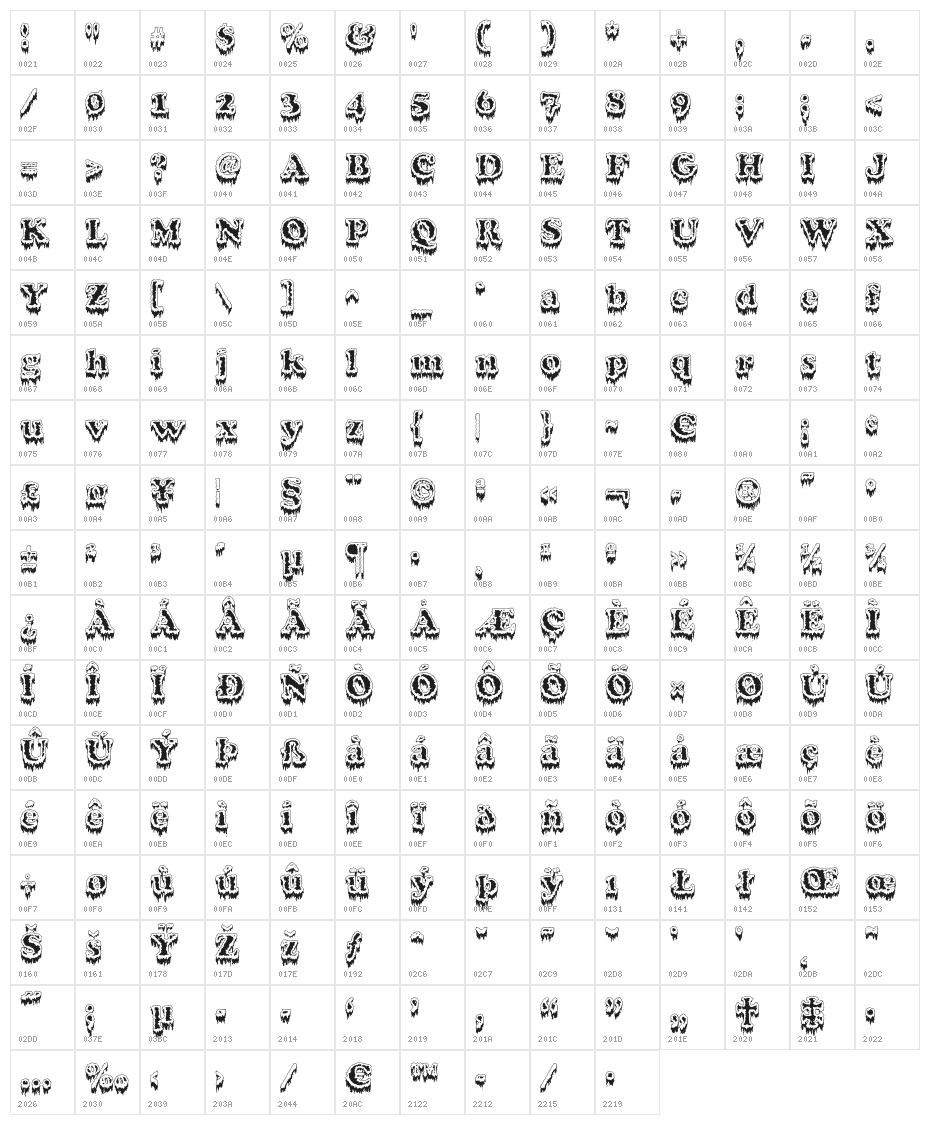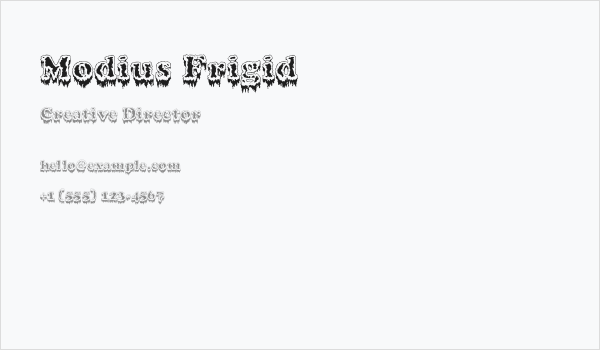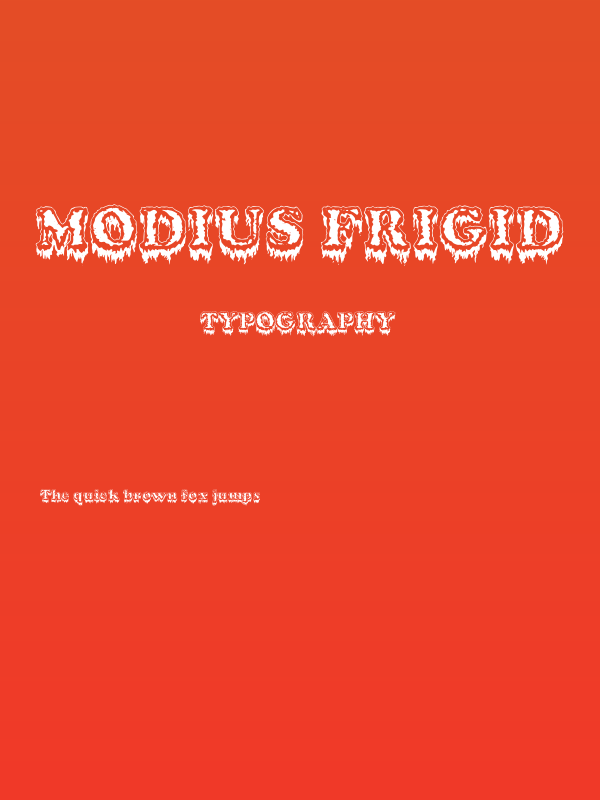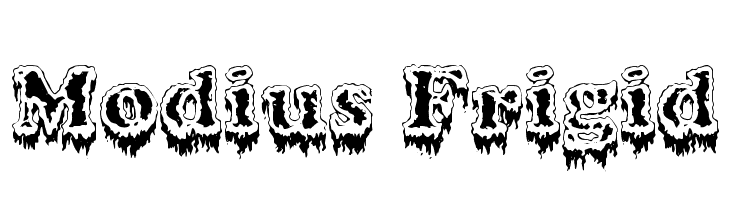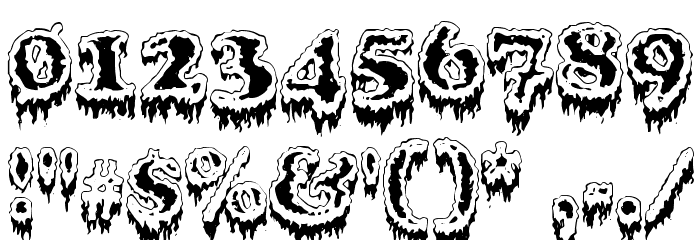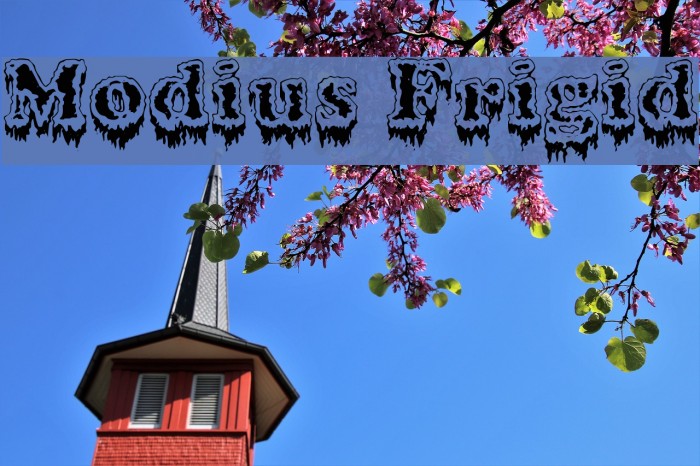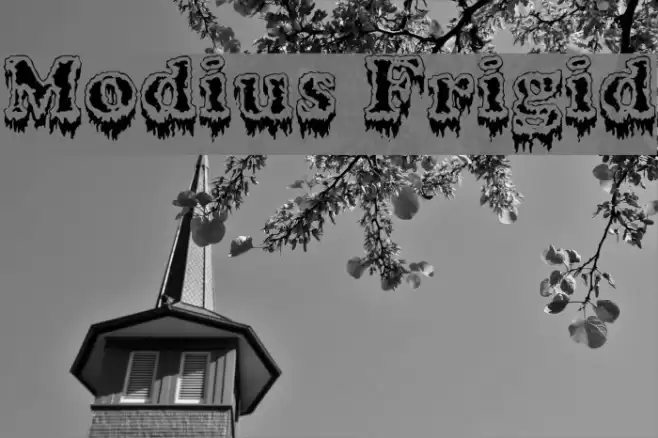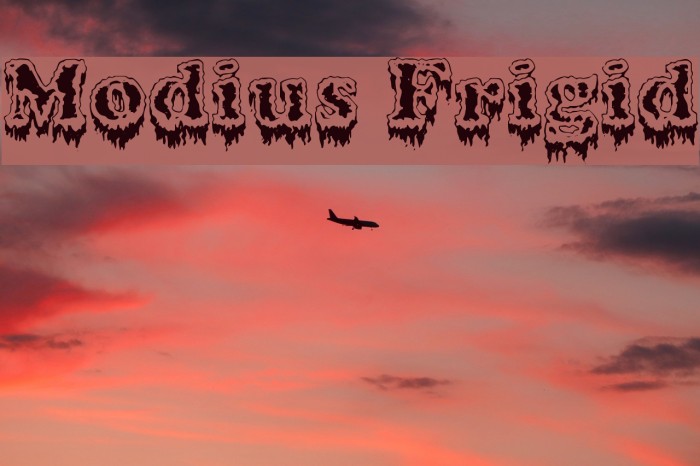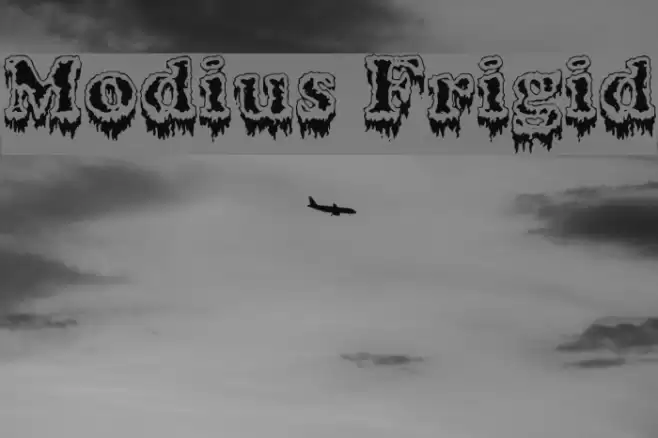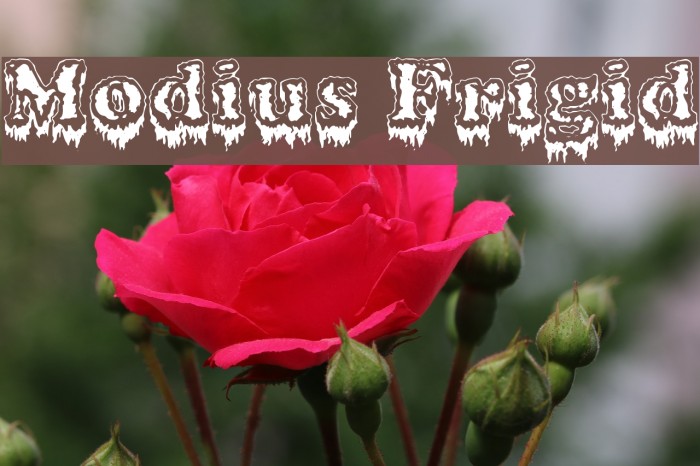
Modius Frigid Font
| Vorgeschlagene Projekte | This font is perfect for creating eye-catching posters, Halloween invitations, winter-themed event flyers, or any project that requires a chilling, dramatic effect. |